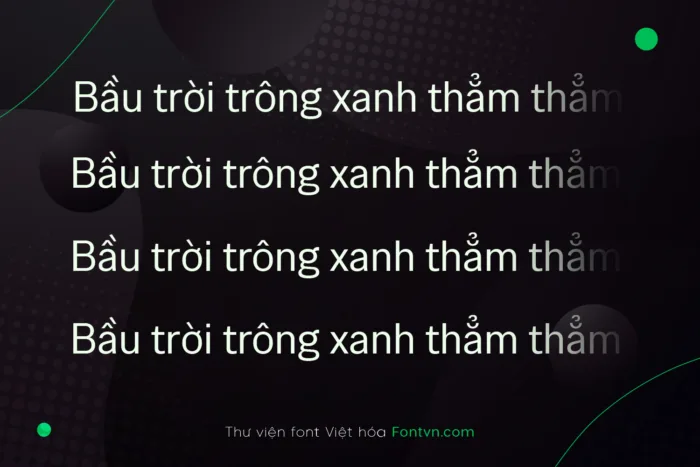
DVN Special Gothic là bản Việt hóa của một kiểu chữ sans-serif mang phong cách hiện đại, giản lược nhưng không hề nhạt nhòa. Thiết kế dựa trên tinh thần Gothic, nhưng được làm mềm lại với các đường cong tròn trịa, khoảng cách thoáng và độ dày trung bình – tạo nên cảm giác thanh lịch, dễ tiếp cận nhưng vẫn giữ được cá tính riêng. Font phù hợp cho tiêu đề, giao diện web, trình bày văn bản hoặc thiết kế thương hiệu theo hướng tối giản. Bản Việt hóa được thực hiện cẩn thận, giữ vững sự nhất quán trong tỉ lệ và nhịp điệu chữ cái, giúp thể hiện tiếng Việt một cách mượt mà và hài hòa. DVN Special Gothic là lựa chọn lý tưởng cho những ai yêu thích sự tinh giản nhưng vẫn muốn mang đến một cảm giác chuyên nghiệp và hiện đại trong thiết kế.